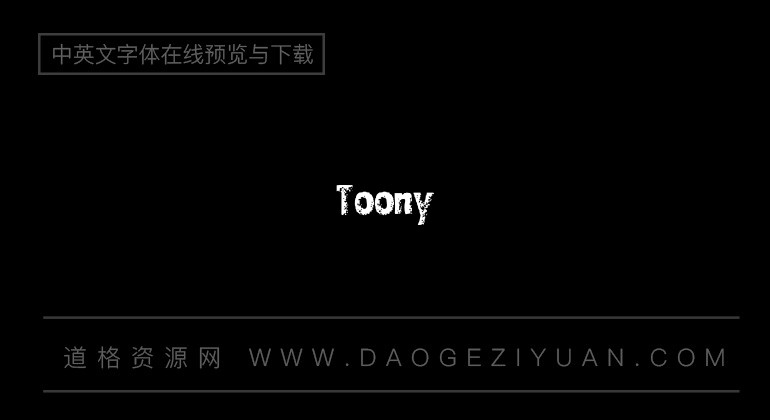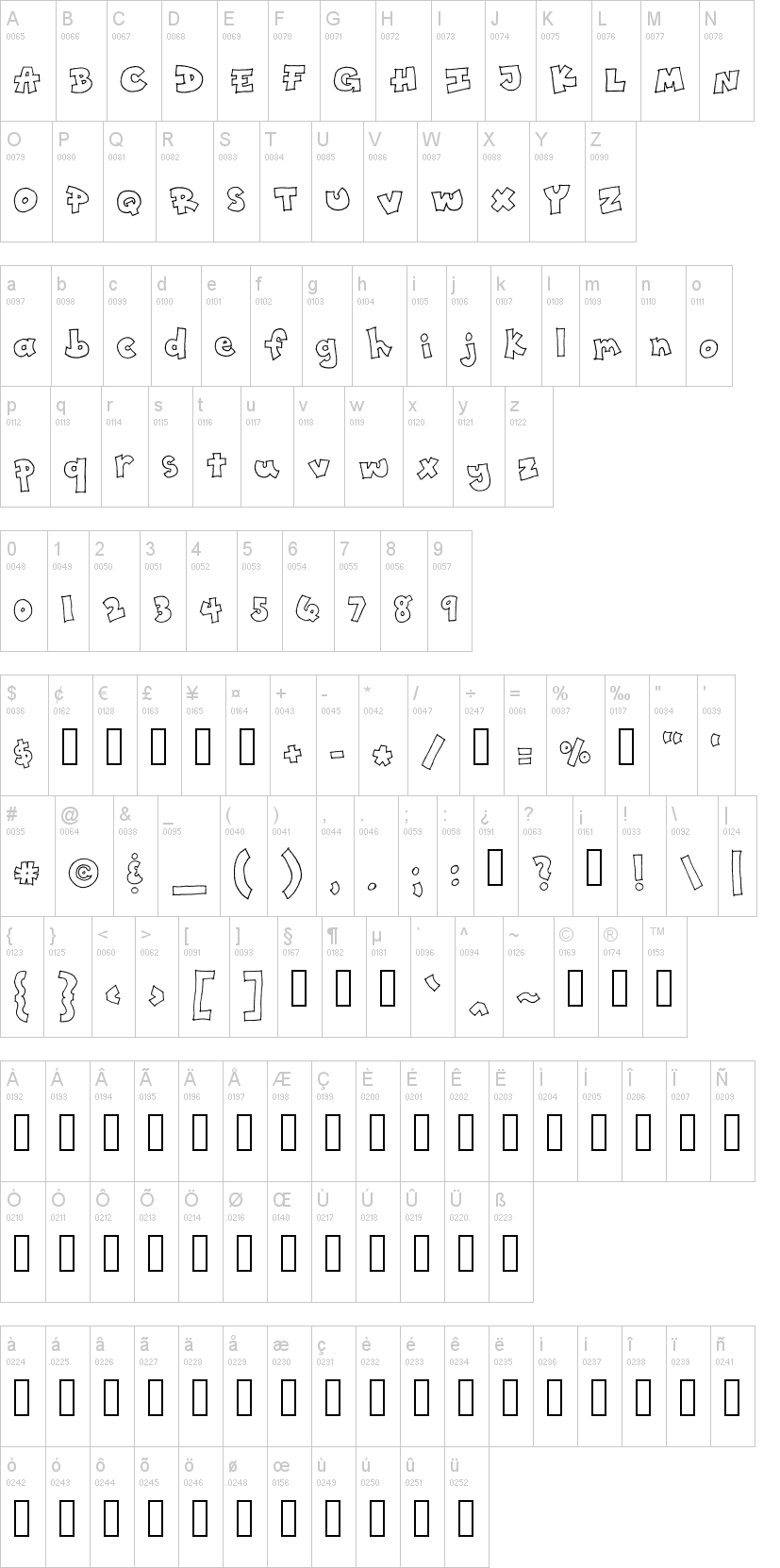
Toony 字体是一种带有漫画或卡通风格的字体,由设计师 Agga Swist'blnk 创造。这种字体有一个非常清晰和简单的外观,适合用于设计儿童相关的作品、漫画或其他需要呈现卡通风格的项目。 Toony 字体的特点是具有一些圆润的特征,比如字母的末端是弯曲的,字母之间的间距比较大,字母的比例关系也比较大。这些特点使得 Toony 字体非常可读,而且不会显得太过于正式,非常适合于表达可爱和幽默的氛围。 Toony 字体可以用于各种设计领域,例如海报、标志、包装等。它也可以用于网页设计和移动应用程序等数字设计领域。因其独特的卡通风格,Toony 字体通常会引起人们的注意,因此适用于需要突出品牌或信息的设计项目。内容介绍
Toony是一款非常不错的手写艺术字体,具有很好的视觉感,适合于文化类的宣传设计、商业类品牌的广告和产品包装设计以及个性化文字排版等较多场景。